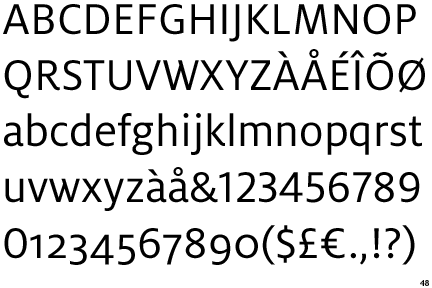
Grotesk mit geschwungenem R?
kennt hier jemand zufällig eine Groteskschrift, die ein R mit so einem geschwungenem Abstrich hat, ähnlich wie bei der Legacy Sans (siehe Bild), aber insgesamt etwas straffer und klarer ist?
Die John Sans hat einen klitzekleinen Aufschwung … kaum sichtbar, aber vorhanden
Die Cronos geht auch ein ganz klein wenig in die Richtung …
ja, aber nicht genug.
ich habe aber inzwischen gefunden, was ich suchte:
[specimen=R:1gbmjd0e]16249[/specimen:1gbmjd0e]
... ich wusste, dass ich kürzlich so ein R bei einer dieser neuen Sans-Fonts gesehen habe, kam aber nicht auf den Namen.
ja, auf die bin ich auch gestossen.
allerdings ist der schenkel des R nicht wirklich geschwungen, sondern hat eigentlich nur ein häkchen und die übrigen buchstaben sind völlig daneben.
die parisine plus wäre evtl. noch gegangen, immerhin hat sie nicht diese starken strichstärkenunterschiede der legacy sans, ist aber insgesamt etwas zu verspielt und soft.
ist aber auch egal, da die fedra sans für den zweck super passt.
Obwohl das Ideal schon gefunden wurde, trotzdem noch eine sehr schöne:
FF Milo von Mike Abbink.
Ja, die ist als Schrift sehr gut gelungen.
Wiewohl der Schwung des Versal-R bei der Fedra hübscher ist.
Zwischenzeitlich bin ich auch noch über die Mr Eaves Sans gestolpert:
Verfügt zwar über ein vorbildlich geschwungenes R, kommt aber dennoch nicht in Frage, da es keine Medium gibt.
Auch sehr ähnlich: Kootenay
... interessant. Aber nur ein Schnitt?
Naja. Man kann sie ja mal im Hinterkopf behalten. Vielleicht ist beim nächsten mal durch Zellteilung (oder wie vermehren sich Schriften? :? ) eine ganze Familie entstanden.
Es bleibt also bei der Fedra
Edit: Und damit ich nicht von der Off-Topic-Polizei verhaftet werde, schmeiße ich noch schnell die Karbid ins Rennen, die hat auch ein geschwungenes R.